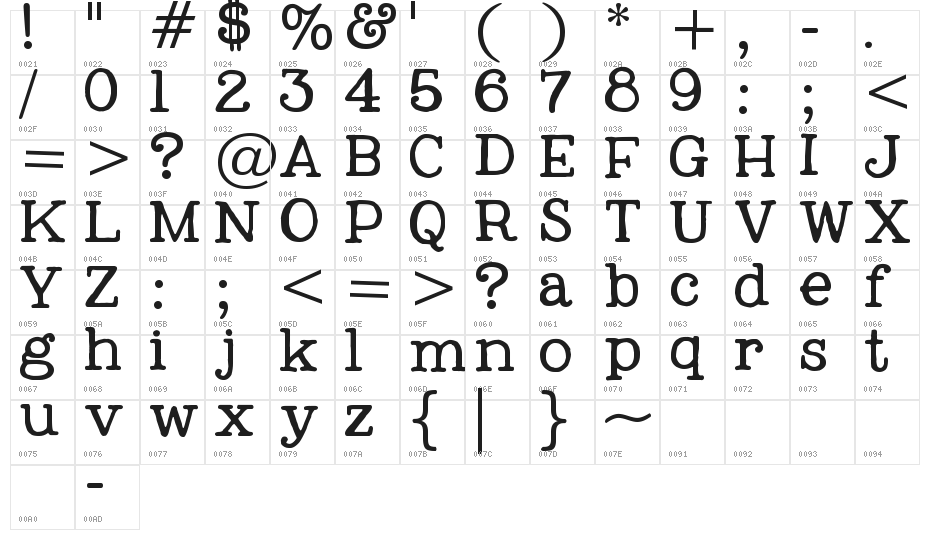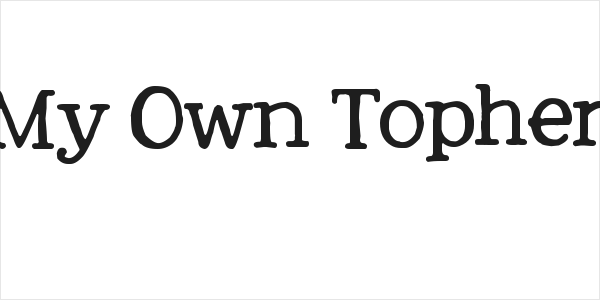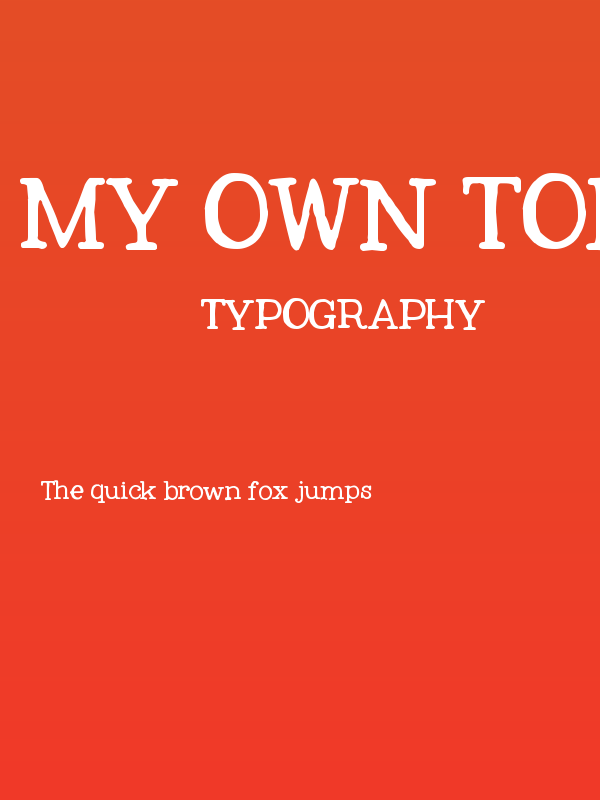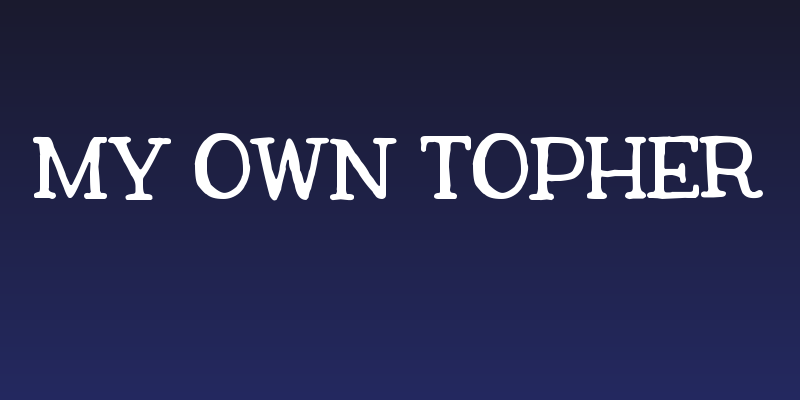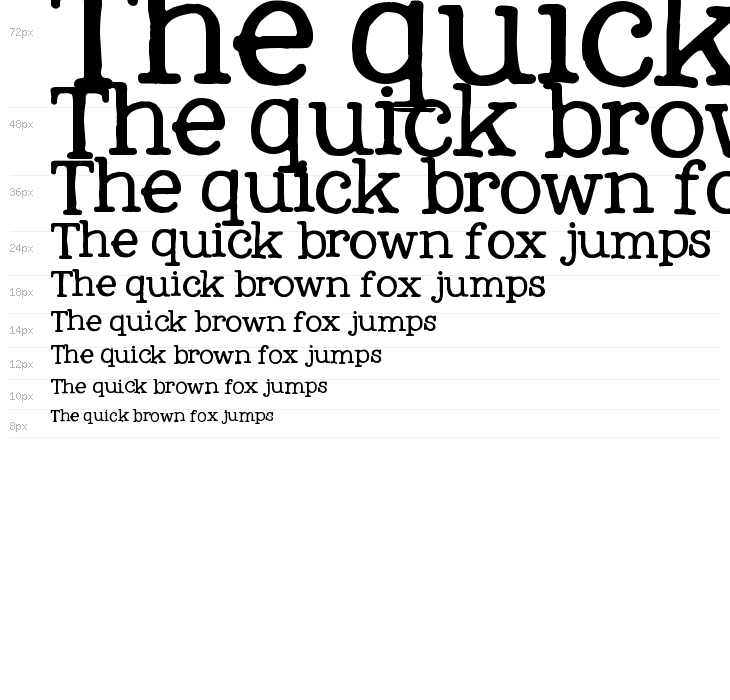
My Own Topher Font
| Progetti proposti | Ideal for retro-themed posters, playful branding, children's books, and creative packaging designs. |
My Own Topher